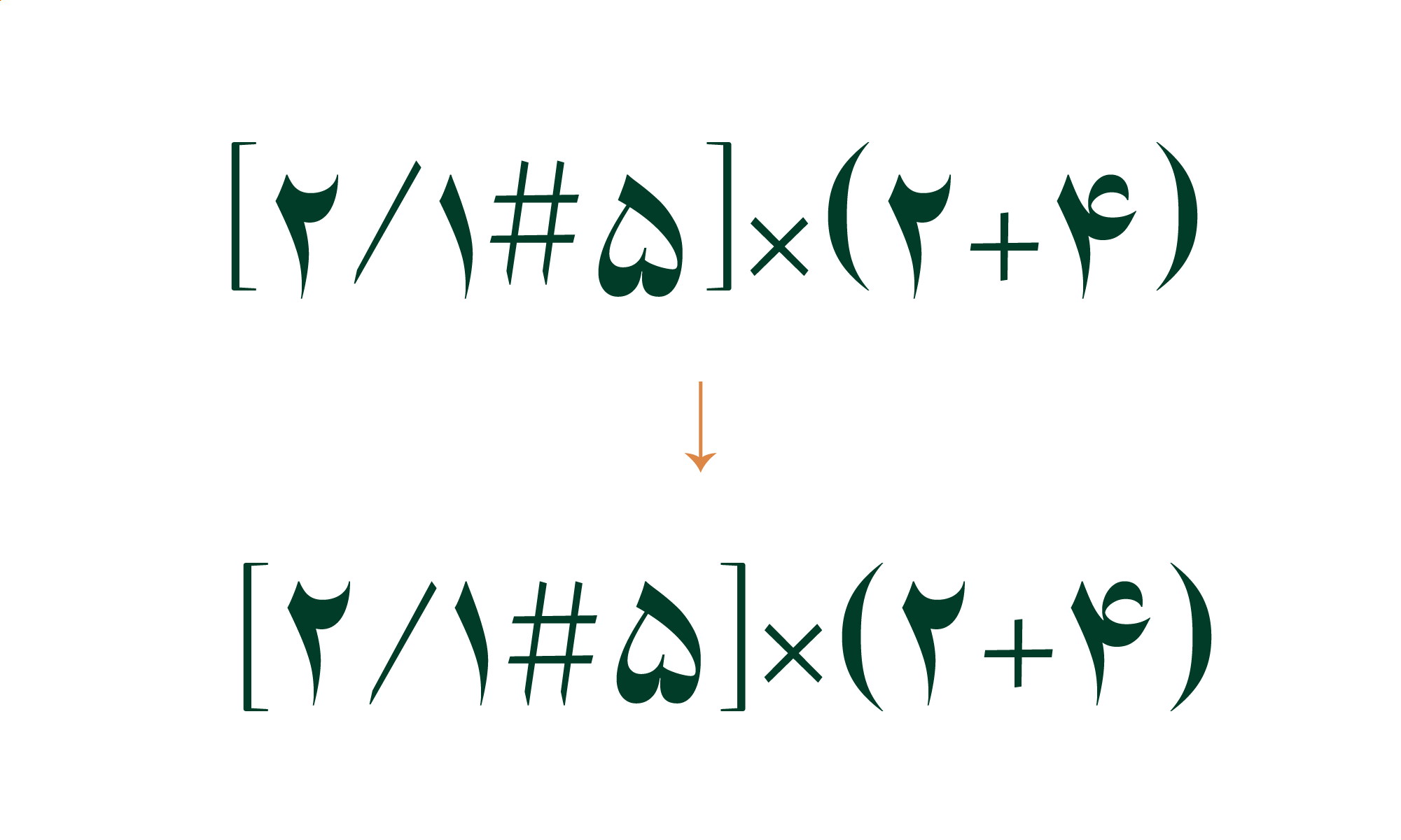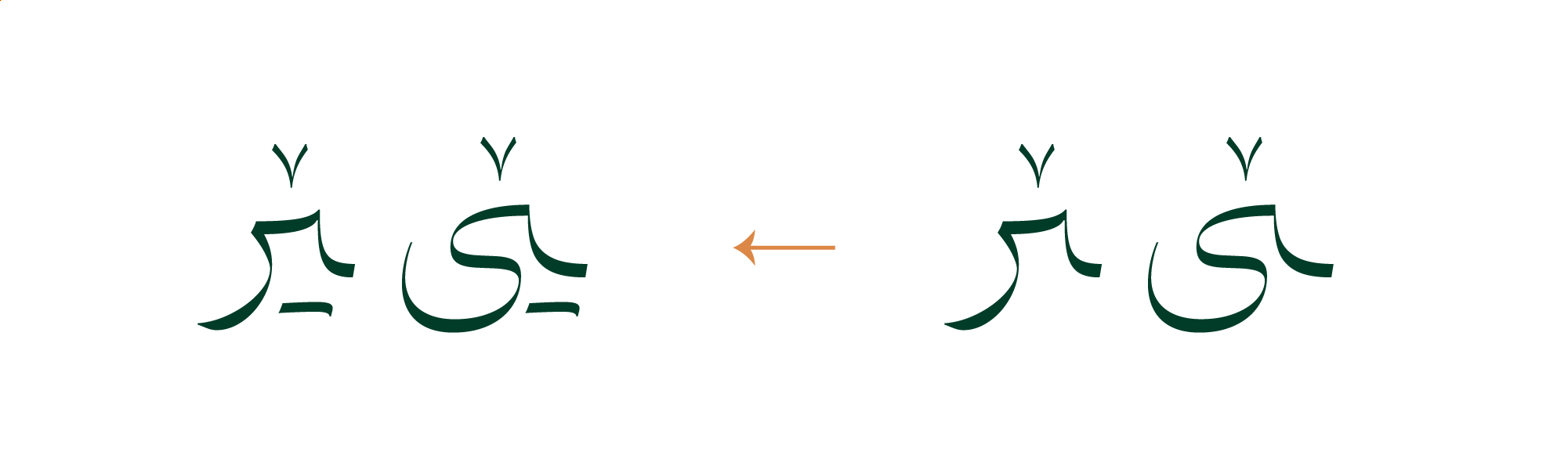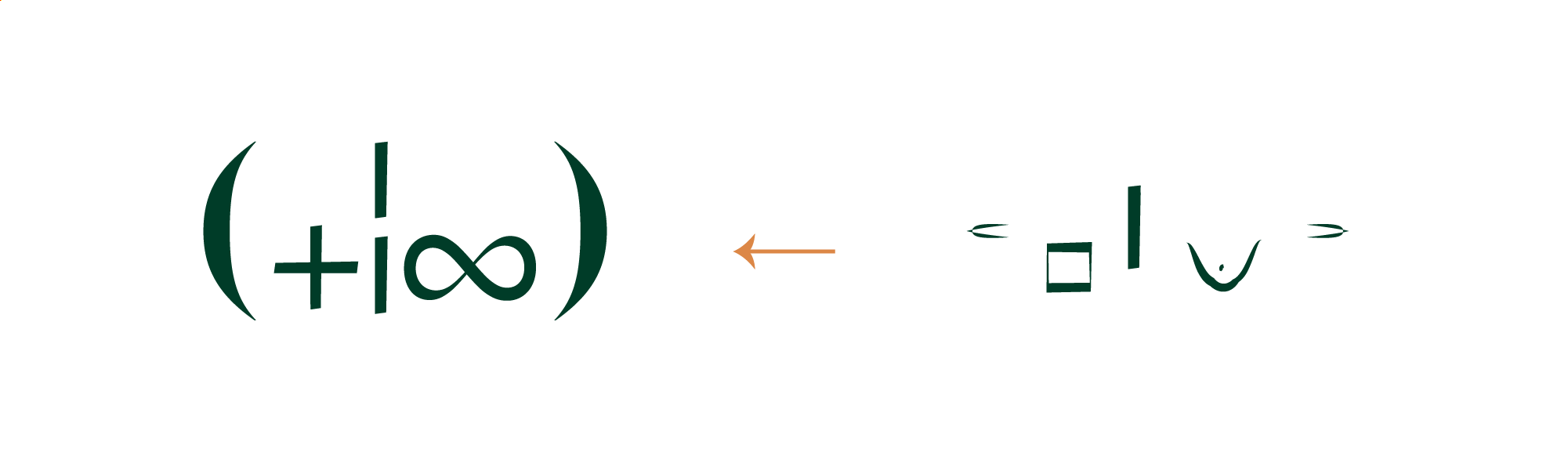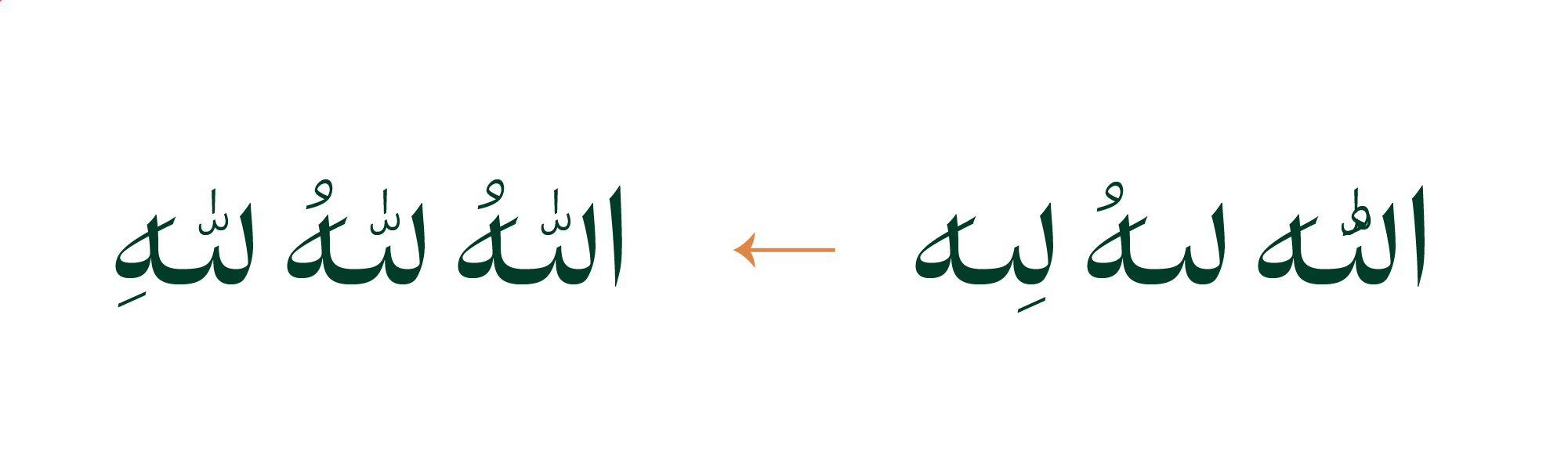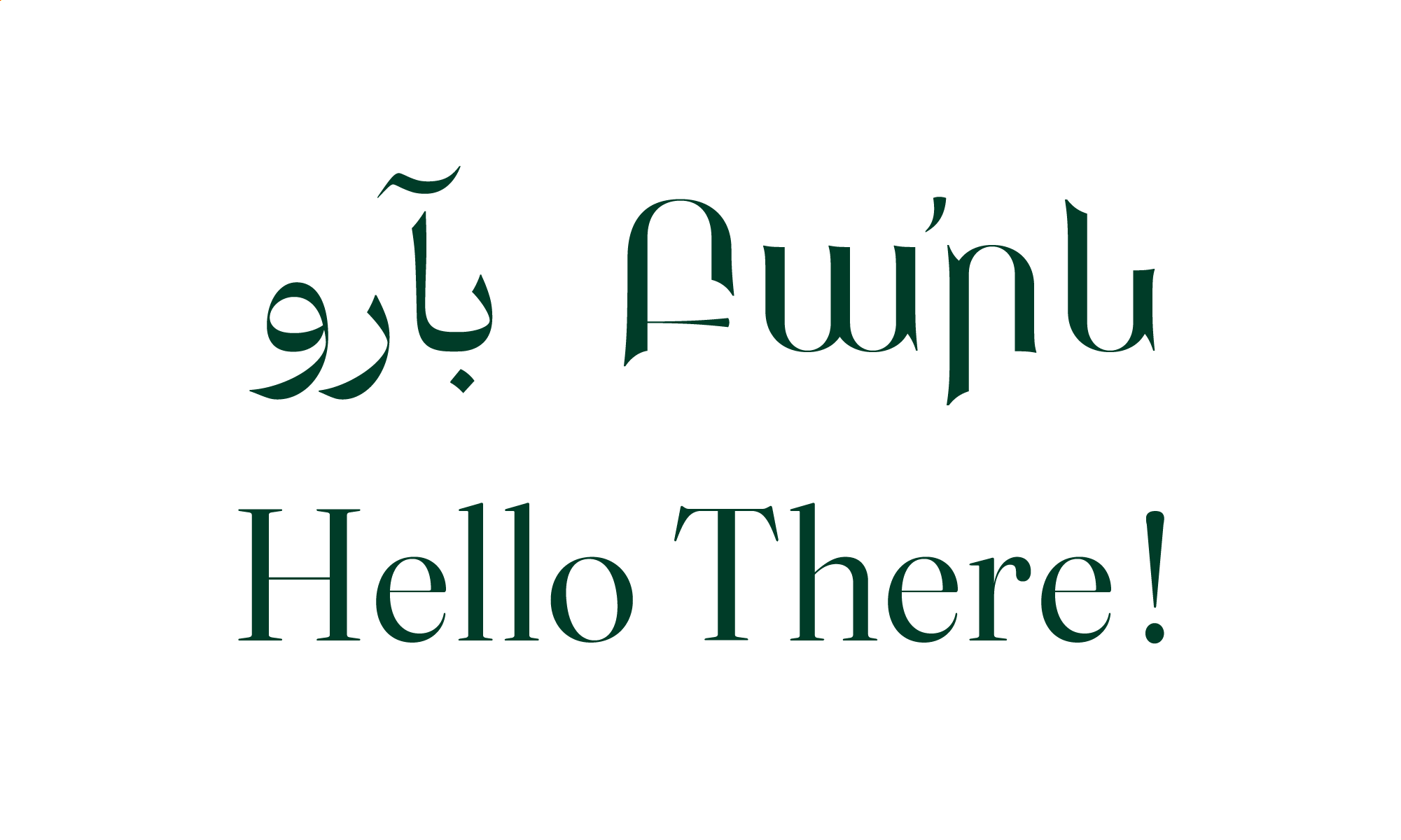
در نسخهی ۳ فونت دوران چه تغییراتی میبینیم؟
مهمترین اتفاق این نسخهی فونت، پشتیبانی دوران از زبان «ارمنی» است. کاراکترهای ارمنی را احسان رودی طراحی کرده است.
1.حالا میتوانید با فونت دوران ارمنی بنویسید.
2.نمادهای «ریال عربستان» و «درهم» برای فونت طراحی شد.
3.با فعال کردن Stylistic Sets ? تراز عمودی علائم ؟!٪؍٬٫/\⁄'#(){}[]|¦ با حروف همآهنگ میشود.
4.ضخامت و جای Underline و Strikethrough تنظیم شد.
5.مشکل فارسی نشدن اعداد در نسخهی FaNum در بعضی از نرمافزارها حل شد.
6.حالا با فعال کردن salt (stylistic alternates)، «ی» معکوس میشود و شکل «ه» تغییر میکند.
7.تغییر شکل «ک م» به حالت کشیدهی آن، به swash منتقل شد.
8.مشکل جا افتادن نقطه در لیگچرهایی که در آن «ێ» وجود دارد اصلاح شد.
9.مشکل نمایش علائم (+¦∞) در وزن Black اصلاح شد.
10.مشکل اعرابهای لله و الله برطرف شد. حالا فقط حرف آخر اعراب میگیرد.
11.به دلیل عدم یکپارچگی پلتفرمهای مختلف در ساپورت کرنینگ اعداد و ایجاد مشکلات، حذف شدند.